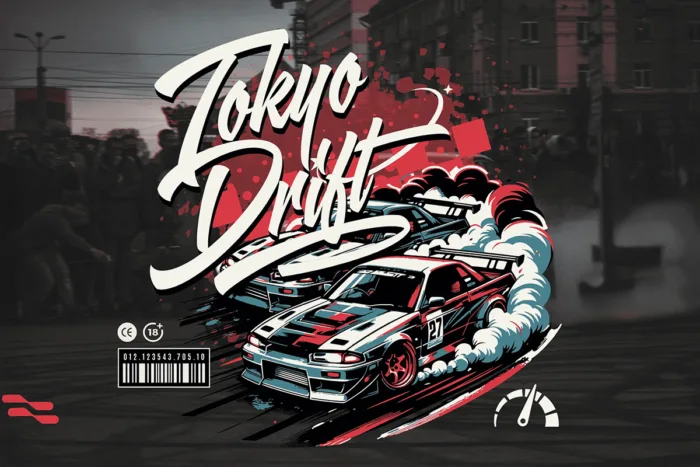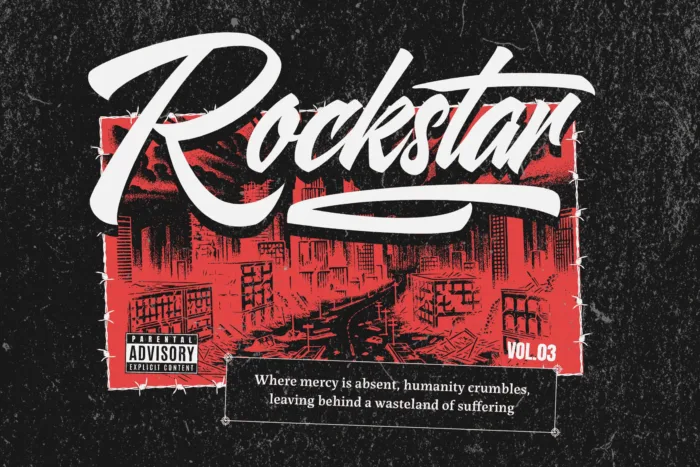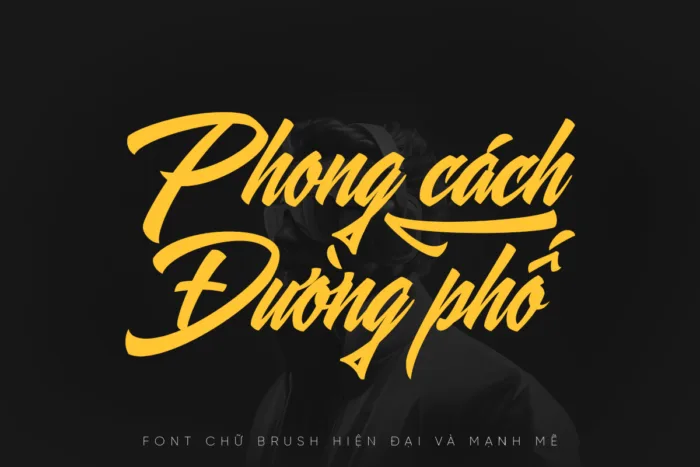
DVN Zentra Brush Việt hóa – Font chữ Brush hiện đại và mạnh mẽ
DVN Zentra Brush là một kiểu chữ script mang phong cách cọ vẽ hiện đại, nổi bật với những đường nét mạnh mẽ, nghiêng dứt khoát và độ tuôn chảy đầy năng lượng. Font mang đến cảm giác hoang dã nhưng vẫn kiểm soát tốt, phù hợp cho các thiết kế đậm chất cá tính như branding thời trang, bìa album, poster sự kiện hay các dự án streetwear.
Phiên bản Việt hóa được tối ưu hoá tỉ mỉ cho hệ thống dấu và chữ tiếng Việt, giữ nguyên tinh thần phóng khoáng của bản gốc trong khi đảm bảo độ dễ đọc và ứng dụng thực tế. Đường gạch chân dài đặc trưng giúp tăng điểm nhấn thị giác, tạo sự nhấn mạnh táo bạo cho tiêu đề hoặc khẩu hiệu.
DVN Zentra Brush là sự kết hợp hoàn hảo giữa nghệ thuật thủ công và chất đường phố hiện đại – đầy cảm xúc, đậm phong cách.